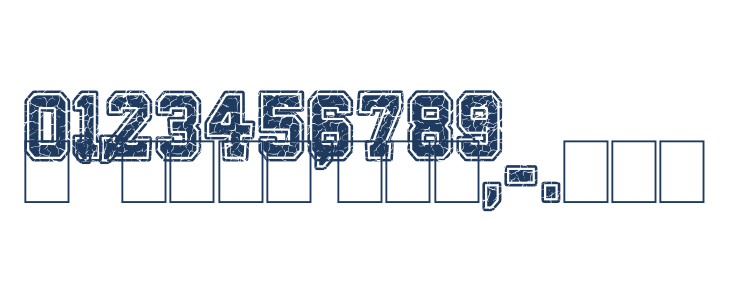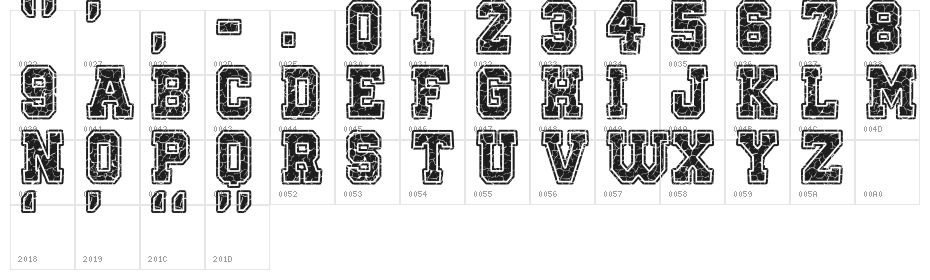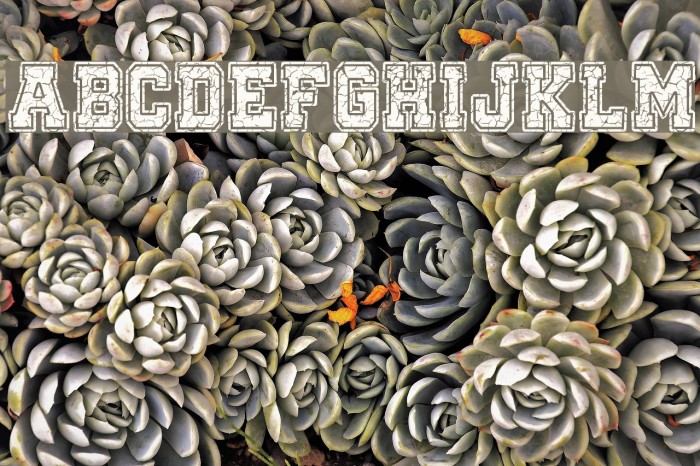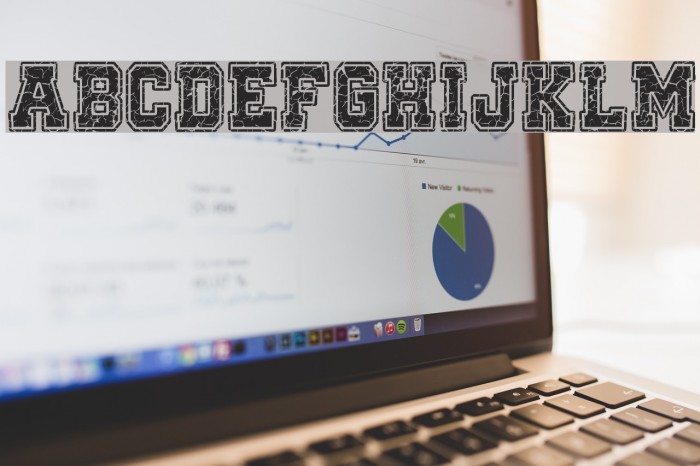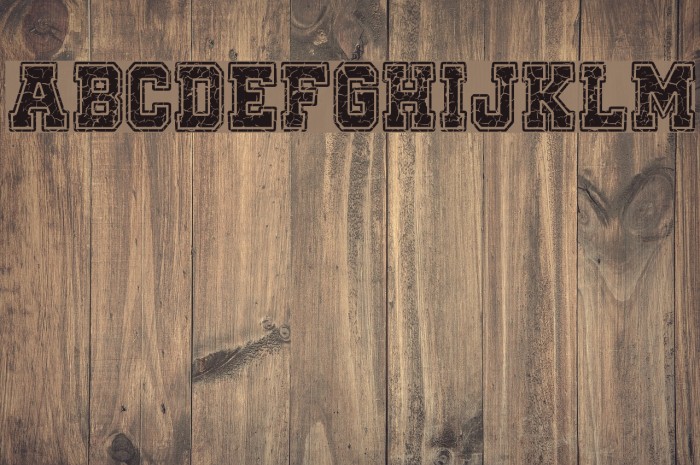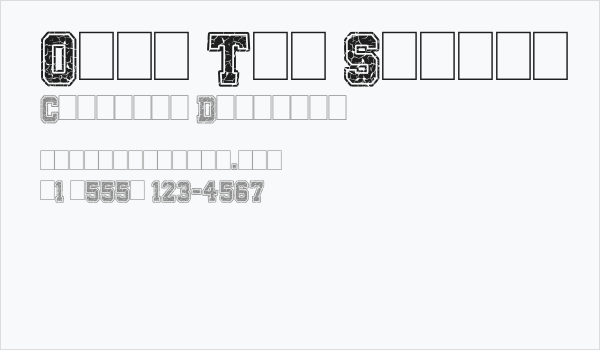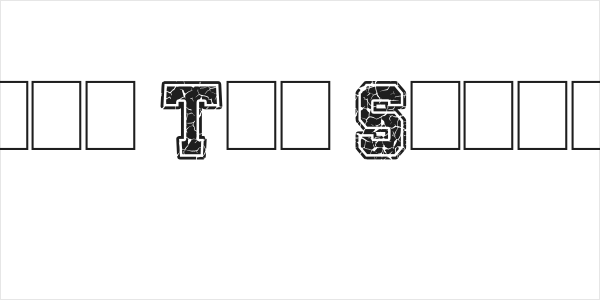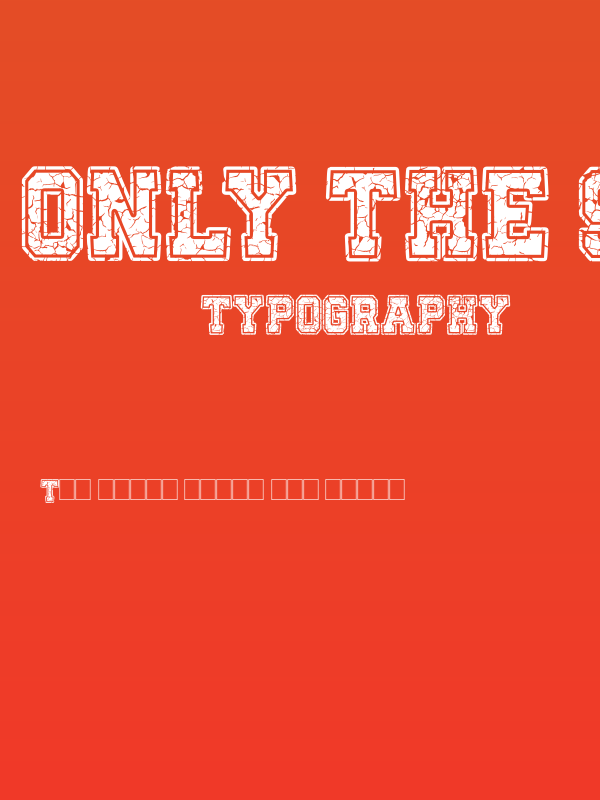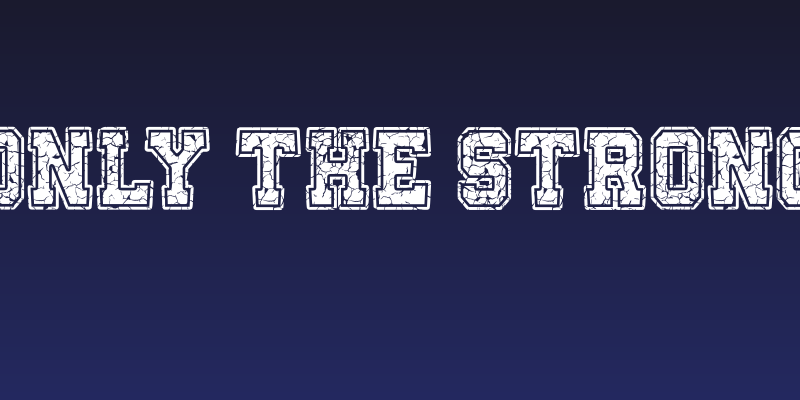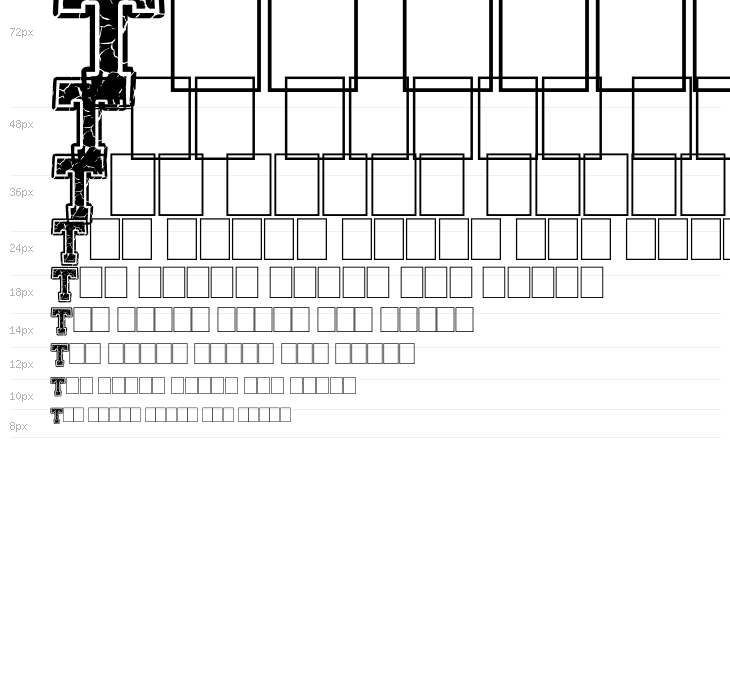
Only The Strong Font
✎ Messy
| الفئات | Messy |
| النمط العام | Vintage |
| مشاريع مقترحة | Ideal for posters, logos, sports team branding, and any design needing a strong, vintage look. |